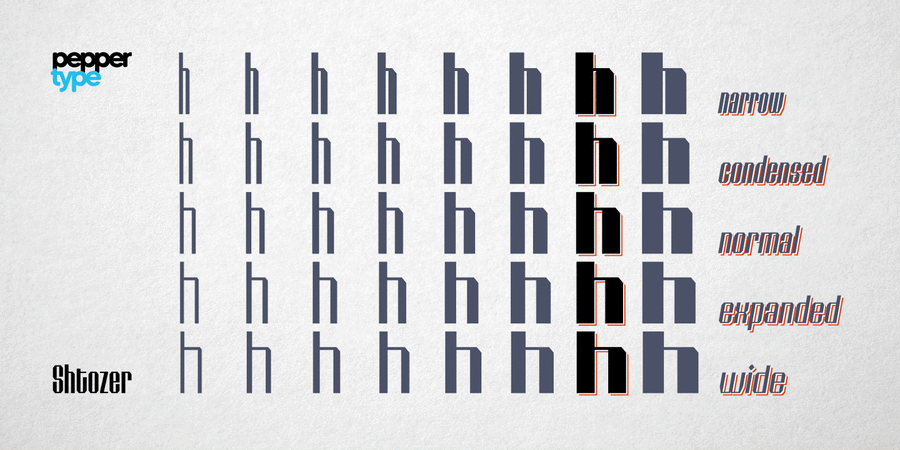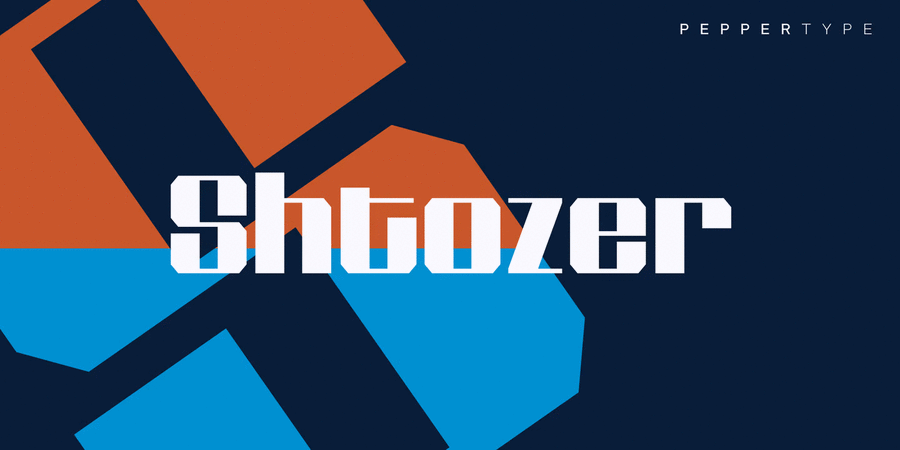
Висококонтрастна версія шрифту Штозер. Акцидентний шрифт у стилі ретро, створений за мотивами 1960-х і 1970-х років, додатково натхненний кириличної в'яззю. Він поставляється у 8 насиченостях, з 5 варіантами ширини для кожної, все супроводжуються відповідними нахиленими версіями – в цілому 80 накреслень. Shtozer – шрифтове сімейство з широким мовним охопленням, що включає кирилицю. Гарнітура також містить безліч функцій OpenType і альтернативних ґліфів для пожвавлення набору. Шрифт розробив Олег Ліщук у 2020 році.
Особливості сімейства шрифтів Shtozer 700Хіт десятиліття:
Асоціації з сімейством шрифтів Shtozer 700Особистість і характер гарнітури:
електронний, молодіжний, рівний, точний, автоматичний, техногенний, твердий, статичний, різкий, чіткий, стійкий, стабільний, прямокутний, міський, машинний, інженерний, урбаністичний, креслярський, надійний, впевнений, сталевий, космічний, переконливий, серйозний, сильний, індустріальний, залізний, мужній, військовий, промисловий, ламаний, незграбний, помітний, яскравий, активний, робочий, кінематографічний, гранчастий, гучний, тісний, чорний, потужний, важкий, оригінальний, брутальний, квадратний, грубий, суворий, холодний, кам'яний, монументальний, агресивний, товстий, наполегливий, масивний, громіздкий, характерний, крутий, хлоп'ячий, запальний, екстремальний, швидкий, гоночний, рішучий, спортивний, енергійний, швидкісний
конструктор, верстат, креслення, інженер, урбаністика, електроніка, авто, інструмент, робот, гра, космос, техніка, автомат, шутер, андроїд, залізо, лего, іграшка, кубики, Місто, архітектура, екскаватор, реклама, тренажери, комп'ютерна гра, кіберспорт, гонки, ралі, формула 1, тачки, спорт, комп'ютер, фантастика, автомобіль, гаджет, авіація, літак, вантажівка, позашляховик, блокбастер, бойовик, екшен, далекобійник, паливо, швидкість, енергетика, скейт, супергерой, шолом, Локдаун, селфі, Доставка Гарнітура має ознаки стилів: